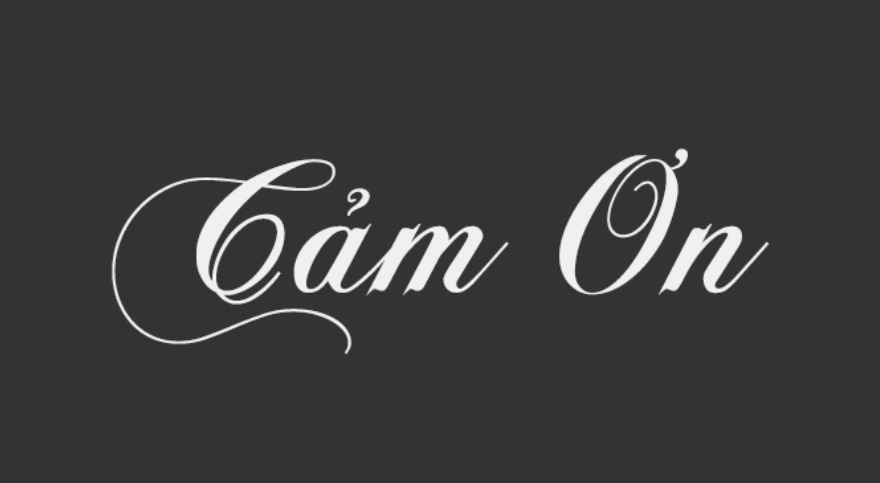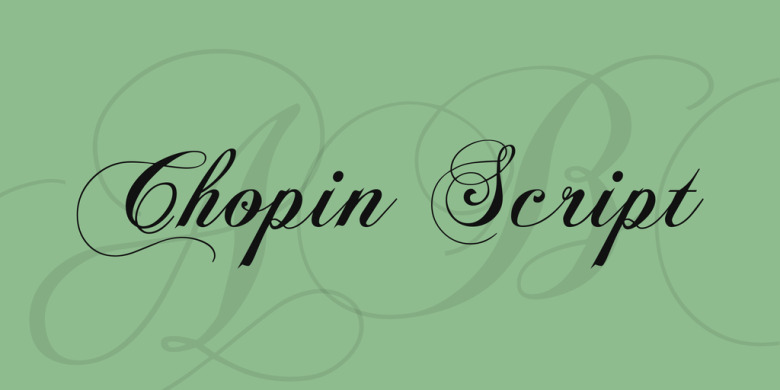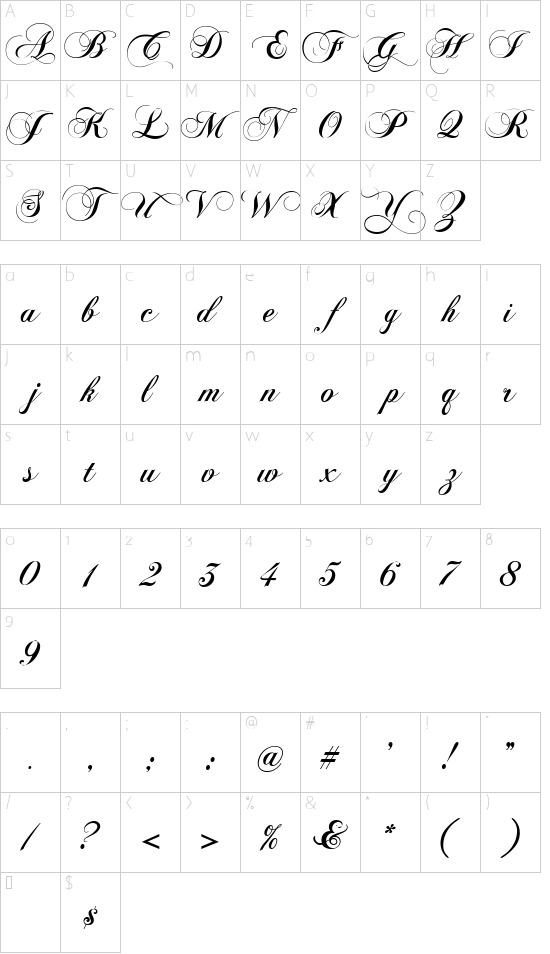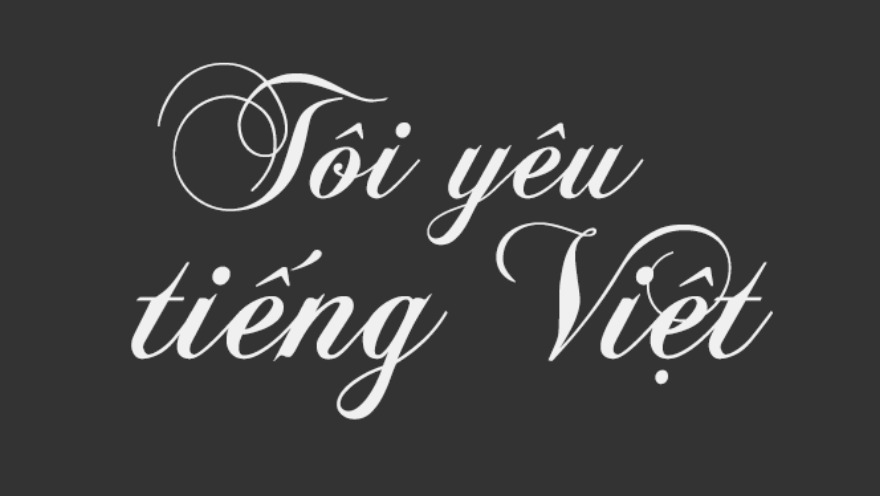
Lỗi gõ dấu tiếng Việt hoặc đường nét uốn lượn quá mảnh bị mất nét khi sử dụng font UVF Chopin Script việt hóa làm giảm sự sang trọng và tính trang trọng của buổi lễ vinh danh hay kỷ niệm. Xưởng In Viva cung cấp bộ font UVF Chopin Script việt hóa chuẩn sắc nét, giúp bạn hoàn thiện các thiết kế tinh tế và chuyên nghiệp.
Font UVF Chopin Script là gì?
UVF Chopin Script là phông chữ thuộc dòng Calligraphy thư pháp hiện đại được yêu thích nhờ vẻ đẹp thanh thoát, uyển chuyển và quý tộc. Lấy cảm hứng từ nét chữ của nhạc sĩ Chopin, phông chữ này mang đến cảm giác như bản nhạc đầy cảm xúc trên từng con chữ. Đây là lựa chọn cho thiết kế chứng chỉ, bằng khen, thiệp cưới hay bao bì yến sào yêu cầu sự trang trọng cao.
Vẻ đẹp của Chopin Script nằm ở sự tương phản cực lớn giữa nét thanh và nét đậm, tạo sự sống động cho bản in. Bản download font UVF Chopin Script tại In Viva đã được việt hóa tỉ mỉ, giúp các dấu tiếng Việt nằm đúng vị trí và không làm gãy các đường uốn lượn của chữ. Nhờ cấu trúc vector chuẩn, phông chữ này hiển thị vô cùng sắc sảo trên các chất liệu giấy mỹ thuật cao cấp tại xưởng in.
Lưu ý: Với Chopin Script, khi in trên gốm sứ, bạn nên tăng độ dày nét Stroke lên khoảng 0.1pt để đảm bảo nét thanh không bị mất sau khi nung ở nhiệt độ cao.
Font UVF Chopin Script được sử dụng như thế nào khi thiết kế và in ấn?
Vẻ cổ điển của Chopin Script nâng tầm giá trị cho mọi ấn phẩm thiết kế gồm có:
- Thiết kế bằng khen và chứng chỉ vinh danh: Mang lại sự trang trọng cao và cảm giác tự hào cho người nhận món quà kỷ niệm.
- Sản xuất hộp đựng yến sào hạng sang: Tên thương hiệu in ép kim nhũ vàng trên nắp hộp cứng tạo nên vẻ đẹp quý phái khó cưỡng.
- In logo lên bộ ấm chén sứ tri ân: Hình ảnh chữ nghệ thuật in nung men sứ Bát Tràng là món quà đối ngoại vô cùng tinh tế và bền bỉ.
- Thiết kế menu tiệc và thiệp VIP: Tạo sự khác biệt cho khách mời thông qua những tà chữ cổ điển sắc sảo trên chất liệu giấy mỹ thuật cao cấp.
Sử dụng font chữ UVF Chopin Script cần lưu ý gì?
Để phông chữ thư pháp Chopin Script hiển thị đẹp trên thành phẩm thực tế, designer cần chú trọng:
- Hạn chế in chữ quá nhỏ: Vì có nhiều nét thanh mảnh, hãy sử dụng cỡ chữ từ 14pt trở lên để không bị mất nét khi in ấn thực tế.
- Tối ưu đường Path cho gia công bế nổi: Kỹ thuật viên sẽ làm mượt mọi điểm neo trong file vector Chopin Script để khuôn bế dập nổi logo hiển thị sắc sảo, không bị rách giấy.
- Lựa chọn mã màu nhũ chuẩn: Khi ép kim, hãy chọn mã nhũ Gold hoặc Bronze để cộng hưởng cùng vẻ đẹp quý tộc của phông chữ này trên hộp quà.
- Kết hợp font chữ không chân: Nên dùng Chopin Script cho tiêu đề và kết hợp cùng font Sans-serif cho nội dung chi tiết để bố cục thông thoáng hơn.
1. Font UVF Chopin Script việt hóa có đủ dấu “đ, ư, ơ” không?
Có, bản việt hóa tại In Viva đã được xử lý hoàn chỉnh bảng chữ cái tiếng Việt, đảm bảo gõ văn bản dài không bị lỗi.